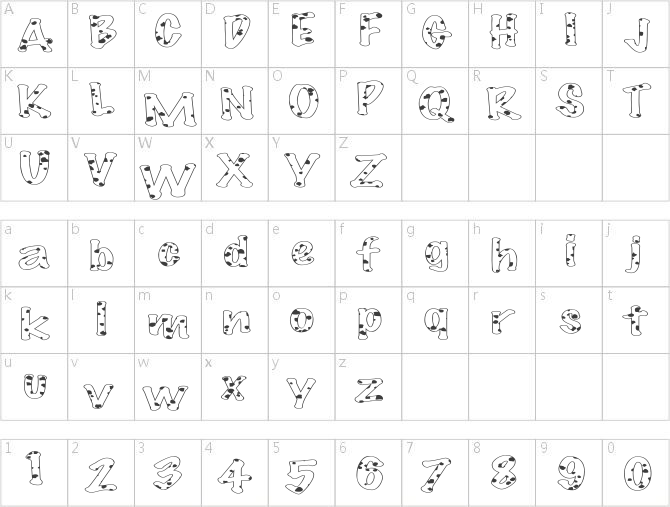
FZ HAND 14 SPOTTED EX 詳情頁(yè)
FZ HAND 14 SPOTTED EX字體字庫(kù)是一款讓人賞心悅目、百看不厭的英文字體,適合各類廣告和產(chǎn)品包裝設(shè)計(jì)應(yīng)用,字體大小0.15MB,格式為ttf字體,上傳用戶是凡塵之間,作者/版權(quán)方為未知